Die 15 besten Fire-Schriftarten 2023 (kostenlos und Premium)
Veröffentlicht: 2023-08-01Sind Sie ein Grafikdesigner und auf der Suche nach der perfekten Feuerschrift, um Ihre Projekte auf die nächste Stufe zu heben? Suchen Sie nicht weiter! In diesem Blogbeitrag gehen wir auf die 15 besten Feuerschriftarten ein, die Ihren Designs eine feurige Note verleihen.
Egal, ob Sie an einem Logo, Poster oder einer Website arbeiten, diese Schriftarten helfen Ihnen dabei, ein visuell beeindruckendes und wirkungsvolles Design zu erstellen.
Nun fragen Sie sich vielleicht: Warum werden Schriftarten abgefeuert? Nun, Feuerschriften sind eine großartige Möglichkeit, Ihren Designs Energie, Leidenschaft und Intensität zu verleihen. Sie können verwendet werden, um Emotionen zu wecken, ein Gefühl der Dringlichkeit zu erzeugen oder einfach eine mutige Aussage zu machen.
Mit der richtigen Feuerschrift können Sie sofort die Aufmerksamkeit Ihres Publikums erregen und einen bleibenden Eindruck hinterlassen.
In diesem Artikel stellen wir die 15 besten Feuerschriftarten vor, die derzeit auf dem Markt erhältlich sind. Wir stellen Ihnen einige interessante Statistiken und Fakten zu jeder Schriftart zur Verfügung, beispielsweise zu ihrer Beliebtheit bei Grafikdesignern, ihrer Vielseitigkeit in verschiedenen Designprojekten und ihren einzigartigen Merkmalen, die sie auszeichnen.
Machen Sie sich also bereit, Ihrer Kreativität mit diesen herausragenden Feuerschriften freien Lauf zu lassen!
Kommen wir nun direkt zur ersten Schriftart auf unserer Liste und erkunden ihre unglaublichen Funktionen und Einsatzmöglichkeiten in Ihren Designprojekten. Machen Sie sich bereit, Ihren Designs ein feuriges Element hinzuzufügen, das Ihr Publikum fesseln und Ihre Arbeit aus der Masse hervorheben wird. Lass uns eintauchen!
Beste Premium-Feuerschriftarten
Möchten Sie Ihren Designs ein Element feuriger Brillanz verleihen? Dann sind Sie bei unserer kuratierten Sammlung der besten Premium-Feuerschriften genau richtig. Diese Schriftarten werden Ihre Projekte mit ihren kühnen und fesselnden Stilen begeistern und dafür sorgen, dass sich Ihre Designs von der Masse abheben.
FEUER
FIRE ist eine erstaunliche Display-Schriftart, die Flammen nutzt, um ein fesselndes und auffälliges Design zu schaffen. Diese einzigartige Schriftart eignet sich perfekt zur Verbesserung von Projekten im Zusammenhang mit Grillabenden, Restaurants oder Lebensmittelunternehmen. Mit seinen feurigen Eigenschaften verleiht FIRE jedem Design einen Hauch von Spannung und Energie.
Einer der Hauptvorteile der Verwendung von FEUER ist seine Fähigkeit, ein Gefühl von Wärme und Aufregung hervorzurufen. Die Flammen in dieser Schriftart wecken eine Assoziation mit Kochen, Grillen und der Freude, sich um ein Feuer zu versammeln.
Es ist die perfekte Wahl, wenn Sie mit Ihrem Design ein Gefühl von Leidenschaft und Energie vermitteln möchten.
Ein weiterer bemerkenswerter Aspekt von FIRE ist seine Kompatibilität mit Designtools wie Figma. Sie können diese Flammenschrift problemlos in Ihre Figma-Projekte integrieren und so ihren feurigen Charme nahtlos in Ihre Designs integrieren.
Ganz gleich, ob Sie Website-Mockups oder Social-Media-Grafiken erstellen, FIRE verleiht Ihren Designs den zusätzlichen Schwung, der sie hervorhebt.
Falo
Falo ist eine bezaubernde Flammenschrift, die Ihren Designs eine feurige Note verleiht. Es ist perfekt, um Ihren Projekten ein einzigartiges und dekoratives Element hinzuzufügen. Ganz gleich, ob Sie Bannerwerbung entwerfen, Veranstaltungseinladungen erstellen oder sogar eine Postkarte gestalten, diese Schriftart ist vielseitig und kann für alle Zwecke verwendet werden.
Mit seinem auffälligen und auffälligen Design wird es mit Sicherheit ein Statement setzen. Verleihen Sie Ihren Projekten mit Falo das gewisse Etwas!
NEROKA
NEROKA ist eine Display-Schriftart, die sich perfekt dazu eignet, Ihren Designprojekten eine feurige Note zu verleihen. Wenn Sie als Grafikdesigner auf der Suche nach einer Schriftart sind, die Ihre Projekte aufwertet und hervorhebt, dann ist NEROKA genau das Richtige für Sie.
Mit seinem kühnen und faszinierenden, von Flammen inspirierten Design verleiht NEROKA jedem Design eine einzigartige Ästhetik. Egal, ob Sie an einem Logo, Poster oder sogar einem Tattoo-Design arbeiten, diese Schriftart verleiht sofort ein Gefühl von Energie und Spannung.
Eine der herausragenden Eigenschaften von NEROKA ist seine Vielseitigkeit. Es kann sowohl für berufliche als auch für private Projekte verwendet werden und ist daher eine gute Wahl für Designer aller Art. Seine auffälligen und auffälligen Buchstabenformen sorgen dafür, dass Ihre Botschaft wahrgenommen und in Erinnerung bleibt.
Feuerbrüder
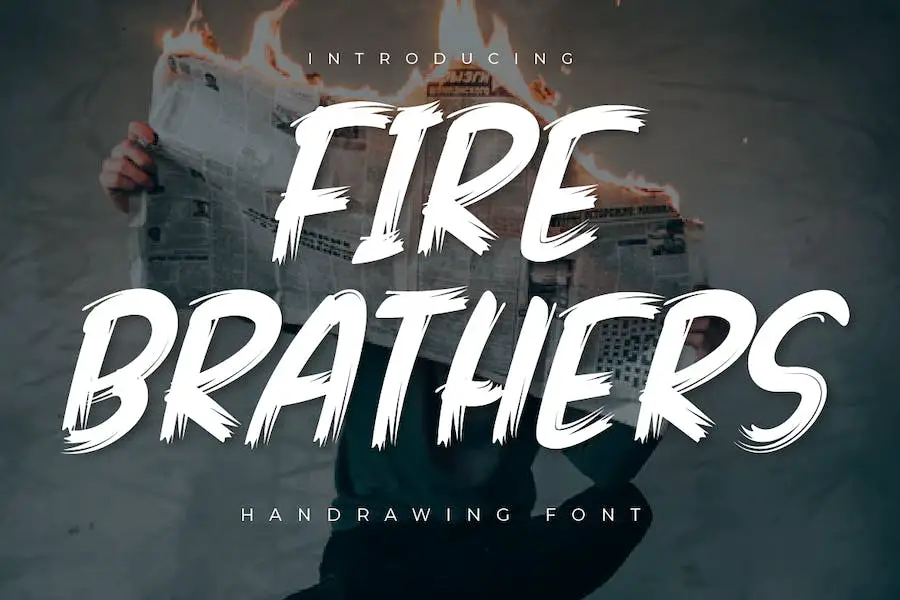
Fire Brathers ist eine Pinselschrift, die speziell entwickelt wurde, um Ihren Projekten einen feurigen Geist zu verleihen. Diese mit viel Liebe zum Detail erstellte Schriftart strahlt Stärke und Charakter aus und sorgt dafür, dass Ihre Arbeit hervorsticht und Aufmerksamkeit erregt.
Mit Fire Brathers können Sie Ihre Projekte mit Begeisterung entfachen und sie unwiderstehlich attraktiv, kraftvoll und einzigartig machen. Es ist die perfekte Wahl für Grafikdesigner, die ihren Kreationen einen Hauch von Feuer und Leidenschaft verleihen möchten.
Ganz gleich, ob Sie an einem Poster, einem Logo oder einem anderen Design arbeiten, Fire Brathers verleiht Ihrer Arbeit das gewisse Etwas.
Got Fire Font
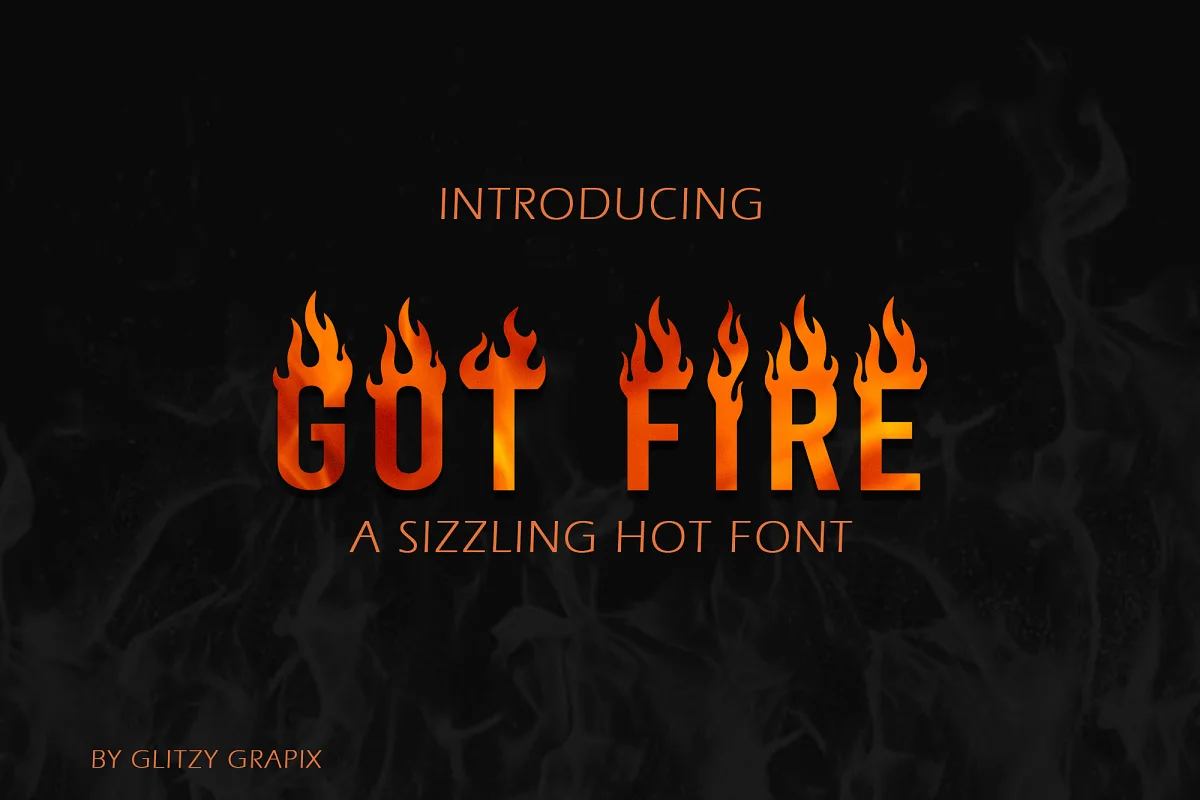
Got Fire Font ist eine brandheiße Display-Schriftart, die jedem Designprojekt eine feurige Note verleiht. Diese Schriftart eignet sich perfekt zum Erstellen von Logos, Überschriften, T-Shirt-Designs, Tassen, Postern, Abzeichen und mehr.
Mit seiner knisternden Ausstrahlung wird es mit Sicherheit Aufmerksamkeit erregen und ein Statement setzen. Egal, ob Sie Ihrem Branding einen Hauch von Wärme verleihen oder Ihren Werbematerialien etwas Feuer verleihen möchten, Got Fire Font ist die ideale Wahl.
Sein fesselndes Design und seine vielseitigen Einsatzmöglichkeiten machen es zu einem Muss für Grafikdesigner, die ihre Projekte aufpeppen möchten. Warum also warten? Entfachen Sie noch heute Ihre Kreativität mit Got Fire Font!
Feuerjungen
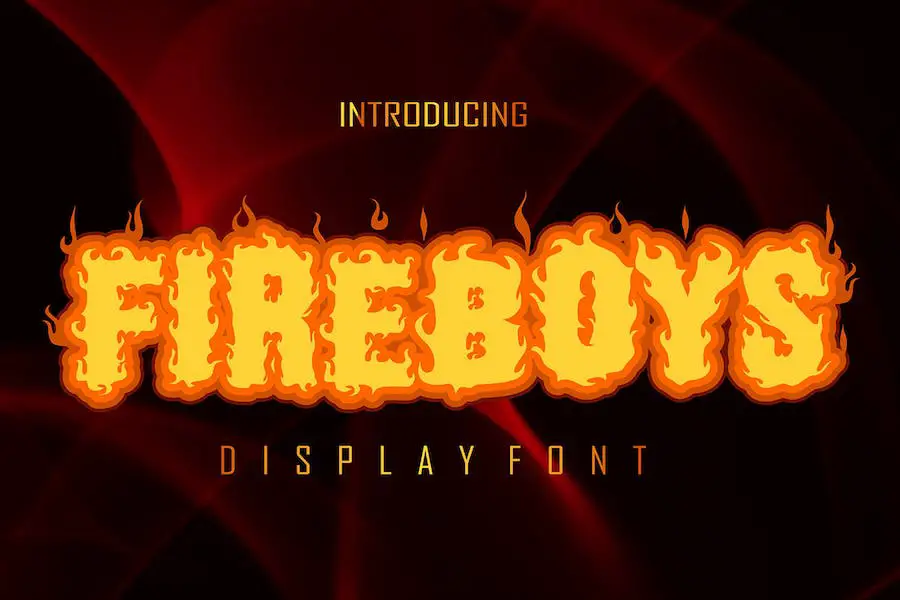
Fireboys Font ist eine bemerkenswerte Display- und Dekorationsschrift, die die Essenz des brennenden Feuers perfekt einfängt. Egal, ob Sie ein Logo erstellen, Kleidung entwerfen oder an Branding-Projekten arbeiten, diese Schriftart verleiht Ihren Designs mit Sicherheit einen Hauch feurigen Charme.
Das Beste daran ist, dass Sie sich um den Aufwand des Zeichnens keine Gedanken machen müssen, da Fireboys Font sofort einsatzbereit ist. Mit seiner einzigartigen Haptik und seinem faszinierenden Aussehen wird es Ihre Kreativität inspirieren und Ihre Bastelprojekte zum Leben erwecken.
Warum also warten? Kaufen Sie noch heute die Schriftart „Fireboys“ und verleihen Sie all Ihren Designwünschen einen flammenden Touch.
Ausgestellt
Flared ist eine einzigartige und ausgefallene Schriftart, die die Essenz von Feuer und Flammen perfekt einfängt. Sein Grunge-inspiriertes Design verleiht jedem Projekt einen Hauch von Robustheit.
Egal, ob Sie als Grafikdesigner an T-Shirt-Typografie, Merchandise-Designs oder einer Logo-Schrift arbeiten, Flared ist die perfekte Wahl. Mit ihrer feurigen Ästhetik hebt diese Schriftart Ihre Designs mit Sicherheit von der Masse ab.
Sein kühner und wirkungsvoller Stil macht es ideal für diejenigen, die harte Schriftarten und Spirit-Schriftarten schätzen. Verleihen Sie Ihren Projekten mit Flared eine feurige Note.
Verbrennen
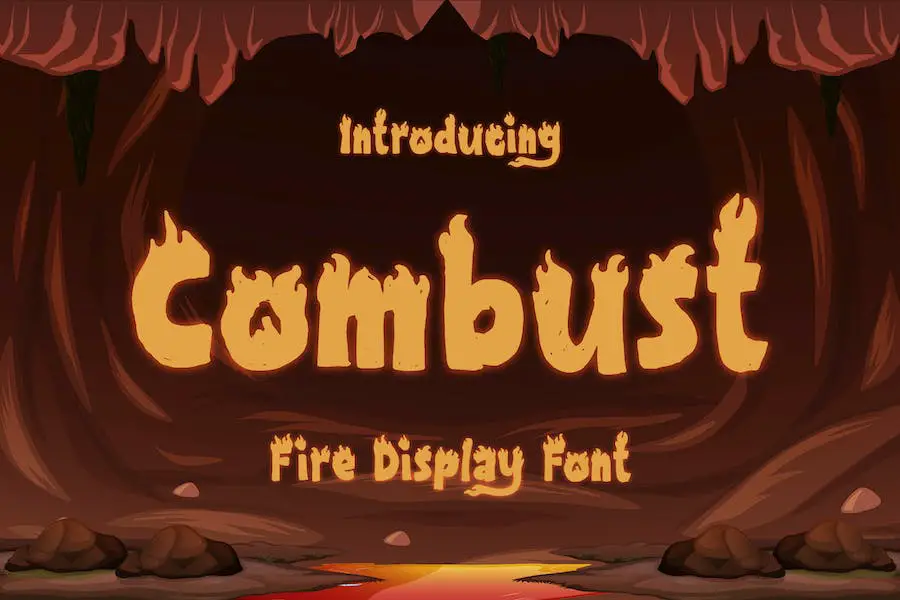
Combust ist eine lebendige und aufregende Displayschrift, die Ihren Designs eine feurige Note verleiht. Mit ihrem modernen und verspielten Stil eignet sich diese Schriftart perfekt, um Ihren Projekten einen Hauch von Intensität zu verleihen.
Egal, ob Sie Poster entwerfen, auffällige Videospiele oder Filmtitel erstellen oder Ihre Marke in sozialen Medien bewerben, Combust ist eine Schriftart, die Aufmerksamkeit erregt.
Combust bietet außerdem eine Reihe von Funktionen, die es unglaublich vielseitig machen. Sein kühner und feuriger Charakter macht es ideal für aufmerksamkeitsstarke Schlagzeilen und Titel.
Egal, ob Sie ein Poster für eine actiongeladene Veranstaltung erstellen oder ein auffälliges Miniaturbild für ein YouTube-Video entwerfen, Combust ist die Schriftart, die Ihren Text zum Hingucker macht.
Feuer
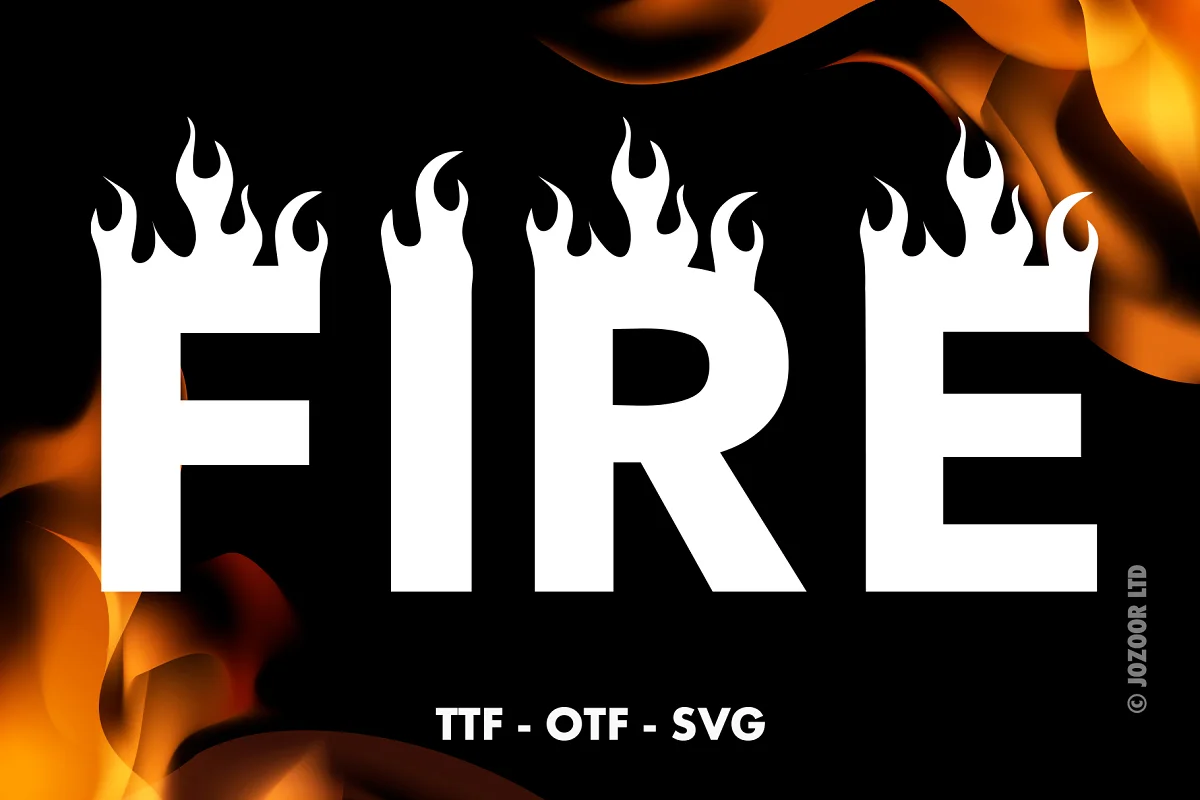
Fire ist eine einzigartige dekorative Schriftart, die Ihren Designprojekten Schwung verleiht. Mit seiner feurigen Ästhetik ist es die perfekte Wahl, um Ihren Kreationen einen Hauch von Glanz und Spannung zu verleihen.
Diese Flammenschrift ist unglaublich vielseitig und lässt sich problemlos in eine Vielzahl von Projekten integrieren. Sein unverwechselbarer Stil verleiht jedem Design ein dynamisches Element und hebt es von der Masse ab.
Mit Fire werden Präsentationen nie langweilig. Verleihen Sie Ihren Folien mit dieser einzigartigen Schriftart einen Hauch von Dramatik und Intensität. Egal, ob Sie einen Vortrag halten, ein Projekt vorstellen oder visuelle Hilfsmittel erstellen, Fire wird Ihr Publikum fesseln und einen bleibenden Eindruck hinterlassen.
Bakar
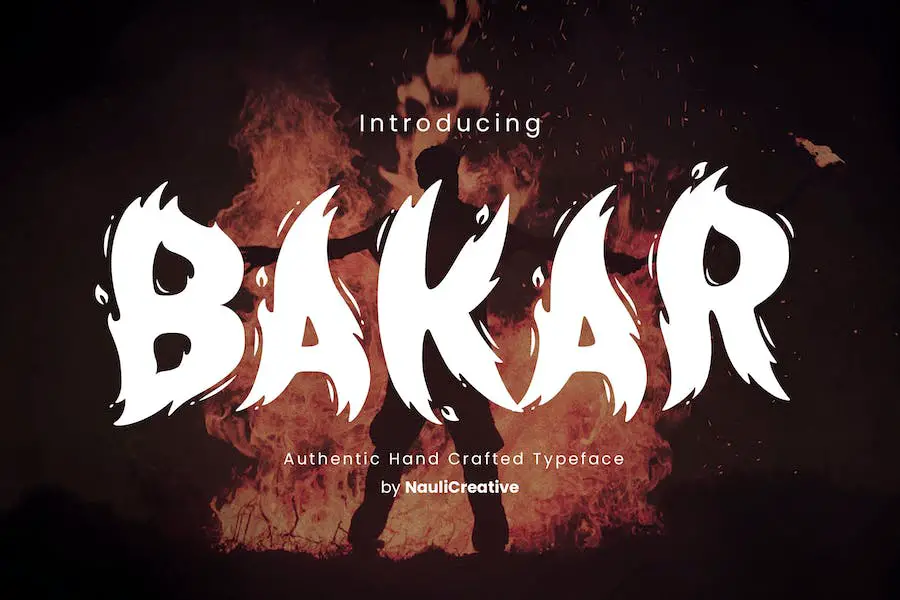
Bakar ist eine fantastische flammende Dekorationsschrift, die sich perfekt dazu eignet, Ihren Projekten eine einzigartige Note zu verleihen.
Diese Schriftart ist unglaublich vielseitig und kann für eine Vielzahl von Zwecken verwendet werden, darunter Bannerwerbung, Veranstaltungen, Grußkarten, Poster, Postkarten, Fotografie, Branding, redaktionelle Inhalte, Zitate, musikbezogene Designs und sogar reisebezogene Materialien. Mit Bakar sind die Möglichkeiten endlos.
Mit seinem ausgefallenen und auffälligen Design wird Bakar Ihre Projekte mit Sicherheit zu etwas Besonderem machen. Egal, ob Sie eine mutige und fesselnde Bannerwerbung erstellen oder Ihrer Grußkarte einen Hauch von Eleganz verleihen möchten, mit dieser Schriftart sind Sie bestens aufgehoben.
Es verleiht jedem Design ein feuriges und unverwechselbares Element und eignet sich daher perfekt für Projekte, die das gewisse Etwas benötigen.
Eines der großartigen Dinge an Bakar ist seine Vielseitigkeit. Es funktioniert gut mit einer Vielzahl von Themen und Stilen, sodass Sie es für eine Reihe verschiedener Projekte verwenden können, ohne befürchten zu müssen, dass es fehl am Platz aussieht.
Beste kostenlose Fire-Schriftarten
Möchten Sie Ihren Designprojekten eine feurige Note verleihen? Dann sind Sie bei unserer handverlesenen Auswahl der besten kostenlosen Fire-Schriftarten genau richtig. Diese Schriftarten verleihen jedem Projekt Wärme und Persönlichkeit, also lassen Sie sich das nicht entgehen! Schauen Sie sich unten unsere kuratierte Sammlung von Feuerschriften an und entfachen Sie noch heute Ihre Kreativität.
Brände
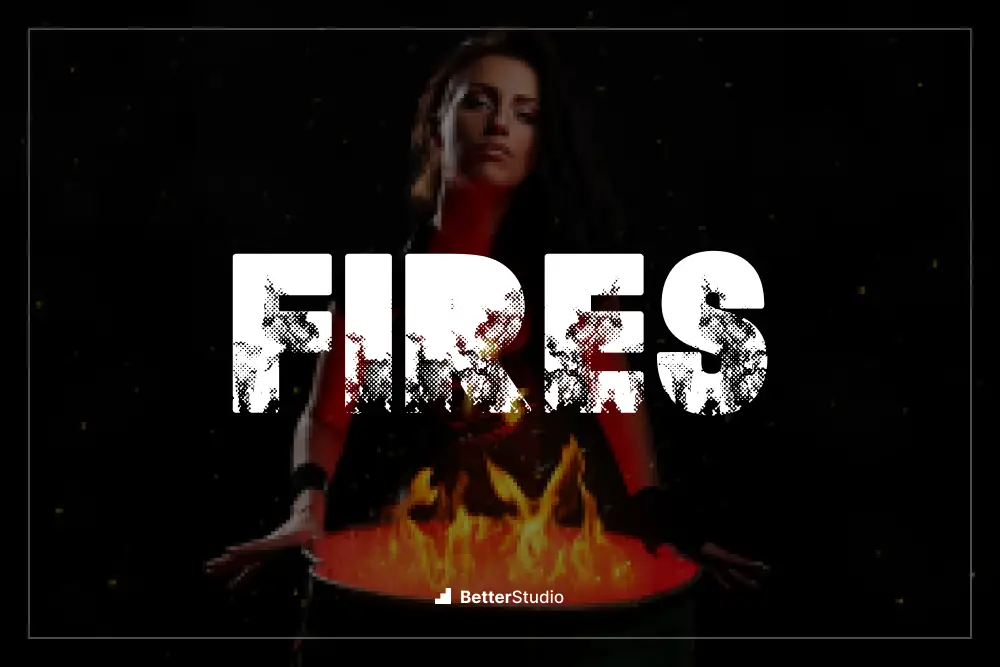
Fires von Billy Argel Fonts ist eine Flammenschrift, die für den persönlichen Gebrauch kostenlos ist. Diese einzigartige Schriftart ist perfekt für Grafikdesigner, die ihren Projekten eine feurige Note verleihen möchten. Mit seinem stilvollen und aufwendigen Design bringt Fires Ihre Designs auf die nächste Stufe.
Die Eigenschaften von Fires heben sie von anderen Feuerschriften ab. Seine detaillierten und realistischen flammenähnlichen Merkmale machen es optisch ansprechend und zu einem Blickfang. Die komplizierten Kurven und Wirbel der Schriftart ähneln tanzenden Flammen und verleihen jedem Design Tiefe und Dimension.
Egal, ob Sie an einem Poster, Logo oder einer Website arbeiten, Fires verleiht Ihrem Projekt einen Hauch von Wärme und Intensität. Sein kühnes und dramatisches Erscheinungsbild eignet sich gut für verschiedene Designstile und wird mit Sicherheit die Aufmerksamkeit des Betrachters auf sich ziehen.
Crush N Burn!
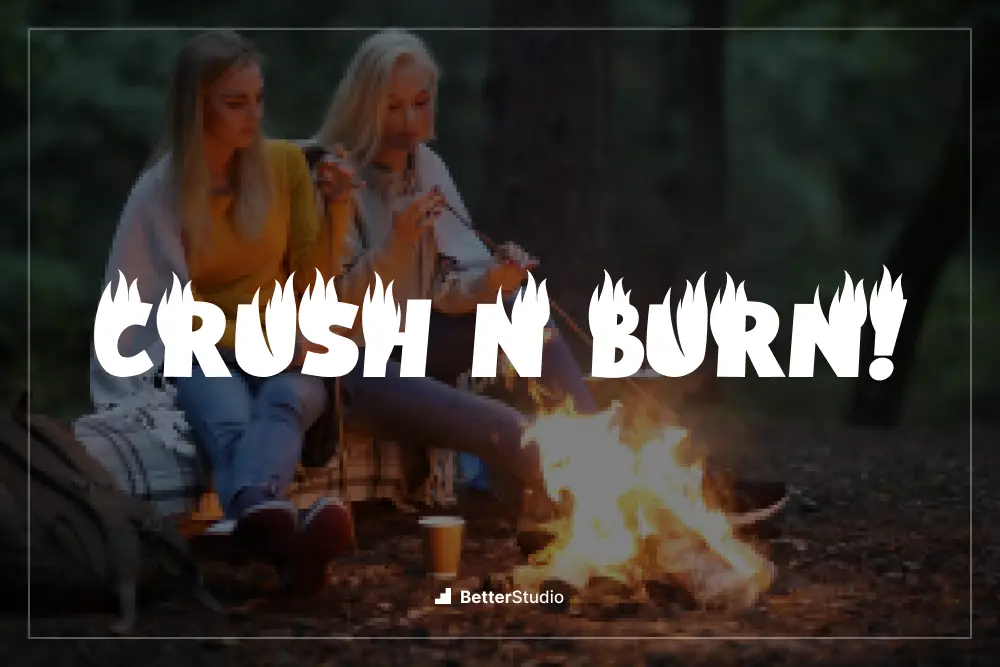
Crush N Burn! ist eine außergewöhnliche Flammenschrift von Vable Studio. Diese Schriftart ist perfekt für Grafikdesigner, die ihren Projekten einen feurigen Touch verleihen möchten.
Es handelt sich um eine vielseitige Schriftart, die für verschiedene Designzwecke verwendet werden kann. Mit seinem fesselnden und wirkungsvollen Design wird es mit Sicherheit Aufmerksamkeit erregen und einen bleibenden Eindruck hinterlassen.
Diese Flammenschrift hat einen einzigartigen und auffälligen Stil, der jedem Design einen Hauch von Intensität verleiht. Egal, ob Sie an einem Poster, Logo oder einer Website arbeiten, Crush N Burn! verleiht Ihrem Projekt eine feurige Note.
Seine kühnen und auffälligen Charaktere setzen garantiert ein Statement und erwecken Ihre Designs zum Leben.
Eines der besten Dinge an Crush N Burn! ist, dass es für den persönlichen Gebrauch kostenlos ist. Das bedeutet, dass Sie diese Schriftart ohne Einschränkungen herunterladen und für Ihre persönlichen Projekte verwenden können.
Es ist eine fantastische Gelegenheit, ohne finanzielle Verpflichtung zu experimentieren und die Möglichkeiten dieser Flammenschrift zu erkunden.
WER IST HEISS
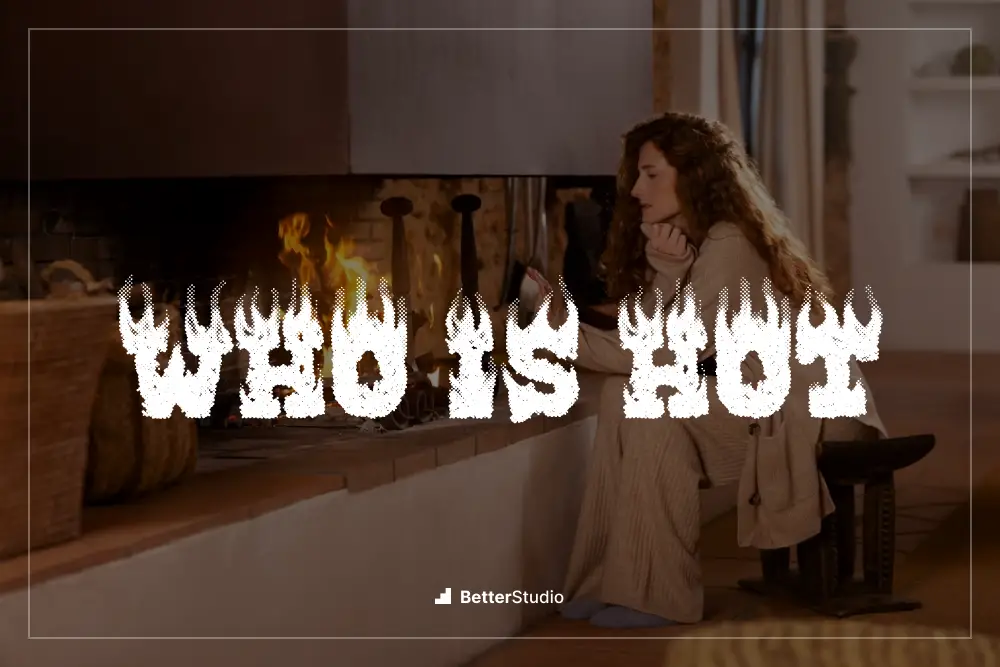
WHO IS HOT ist eine von Billy Argel Fonts erstellte Flammenschrift, die für den persönlichen Gebrauch kostenlos erhältlich ist. Diese Schriftart ist perfekt für Grafikdesigner, die ihren Projekten eine feurige Note verleihen möchten.
Mit WHO IS HOT können Sie das Design Ihrer Kreationen ganz einfach mit den einzigartigen und faszinierenden, von Flammen inspirierten Buchstaben verbessern. Die aufwendigen Details und der kühne Stil der Schriftart heben sie von der Masse ab und sorgen dafür, dass Ihre Designs jedem ins Auge fallen, der sie sieht.
Die Eigenschaften dieser Flammenschrift sind wirklich beeindruckend. Seine scharfen Kanten und feurigen Konturen verleihen jedem Text ein Gefühl von Energie und Intensität.
FAN
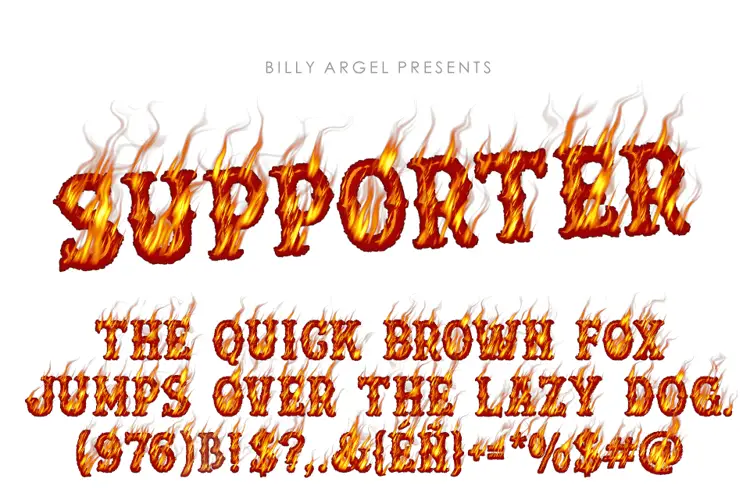
SUPPORTER ist eine bemerkenswerte Flammenschrift, die von Billy Argel Fonts erstellt wurde. Es steht kostenlos für den persönlichen Gebrauch zur Verfügung und ist somit eine ausgezeichnete Wahl für Grafikdesigner, die ihren Projektentwürfen eine feurige Note verleihen möchten.
Diese Flammenschrift ist eine atemberaubende Ergänzung für jedes Design und verleiht Ihren Projekten ein Gefühl von Energie und Intensität. Es fängt die Essenz des Feuers perfekt ein und eignet sich daher ideal für die Erstellung auffälliger Titel, Logos und Branding-Elemente.
Eines der herausragenden Merkmale von SUPPORTER ist die Liebe zum Detail. Jeder Buchstabe ist aufwendig gefertigt, wobei Flammen elegant in das Design integriert sind. Dadurch wird sichergestellt, dass jeder Charakter hervorsticht und einen bleibenden Eindruck bei Ihrem Publikum hinterlässt.
BRENNENDER HAMMER
BURNING HAMMER ist eine auffällige Flammenschrift von PutraCetol Studio, die für den persönlichen Gebrauch erhältlich ist.
Diese Schriftart ist perfekt für Grafikdesigner, die ihren Projekten eine feurige Note verleihen möchten. Mit seinem kühnen und auffälligen Design wird BURNING HAMMER mit Sicherheit ein Statement setzen.
Die Eigenschaften der Schriftart BURNING HAMMER sind wirklich beeindruckend. Seine aufwendigen Details und realistischen Flammeneffekte verleihen jedem Design ein dynamisches und kraftvolles Aussehen.
Diese Schriftart ist vielseitig und ermöglicht es Designern, sie für verschiedene Zwecke wie Logos, Poster und Titel zu verwenden, was sie zu einer wertvollen Ergänzung ihrer Schriftartensammlung macht.
Die Schriftart BURNING HAMMER bietet eine Reihe von Schriftarten und -optionen und gibt Designern die Flexibilität, die Schriftart auszuwählen, die am besten zu ihrem Projekt passt. Ganz gleich, ob es sich um eine kräftige und wirkungsvolle Überschrift oder einen dezenten, von Flammen inspirierten Akzent handelt, diese Schriftart hat alles.
Häufig gestellte Fragen
Feuerschriften sind eine Sammlung von Typografiestilen, die Flammen oder Feuer ähneln. Diese Schriftarten sollen Texten einen feurigen und intensiven Effekt verleihen und eignen sich daher perfekt für verschiedene Designs wie Poster, Logos, Banner und mehr.
Fire-Schriftarten können auf vielfältige kreative Weise eingesetzt werden. Sie können verwendet werden, um auffällige Schlagzeilen zu erstellen, Einladungen oder Veranstaltungsflyern eine dramatische Note zu verleihen, Social-Media-Grafiken aufzuwerten oder sogar persönliche Kunstwerke individuell anzupassen. Die Möglichkeiten sind endlos!
Ja, viele Fire-Fonts verfügen über Lizenzen, die eine kommerzielle Nutzung ermöglichen. Es ist jedoch wichtig, die spezifischen Lizenzbedingungen für jede Schriftart zu prüfen, bevor Sie sie in einem kommerziellen Projekt verwenden.
Für einige Schriftarten ist möglicherweise eine Namensnennung erforderlich oder es gelten Einschränkungen. Überprüfen Sie daher immer die Lizenzdetails, um die Einhaltung sicherzustellen.
Abschluss
Um es noch einmal zusammenzufassen: In diesem Artikel haben wir die 15 besten Fire-Schriftarten besprochen, die Grafikdesigner zur Verbesserung ihrer Projektdesigns verwenden können. Wir haben eine Vielzahl von Optionen untersucht, jede mit ihrem eigenen einzigartigen Stil und ihrer eigenen Ästhetik.
Egal, ob Sie nach einer kräftigen und wirkungsvollen Schriftart oder einer subtileren und künstlerischeren Option suchen, in dieser Liste ist für jeden etwas dabei.
Wenn Sie tiefer in die Welt des Designs eintauchen und weitere verwandte Tutorials entdecken möchten, schauen Sie sich unbedingt den BetterStudio-Blog an. Wir verfügen über eine Fülle von Ressourcen, die Ihnen dabei helfen können, Ihre Designfähigkeiten zu verbessern und Ihre Kreativität anzuregen.